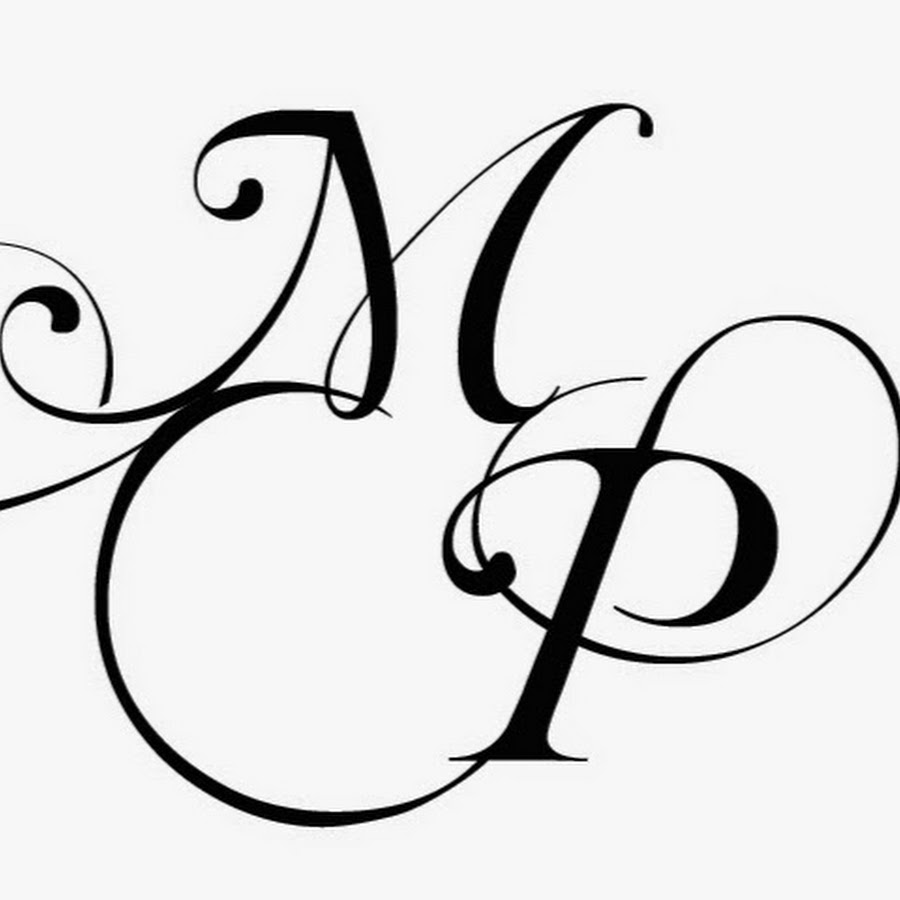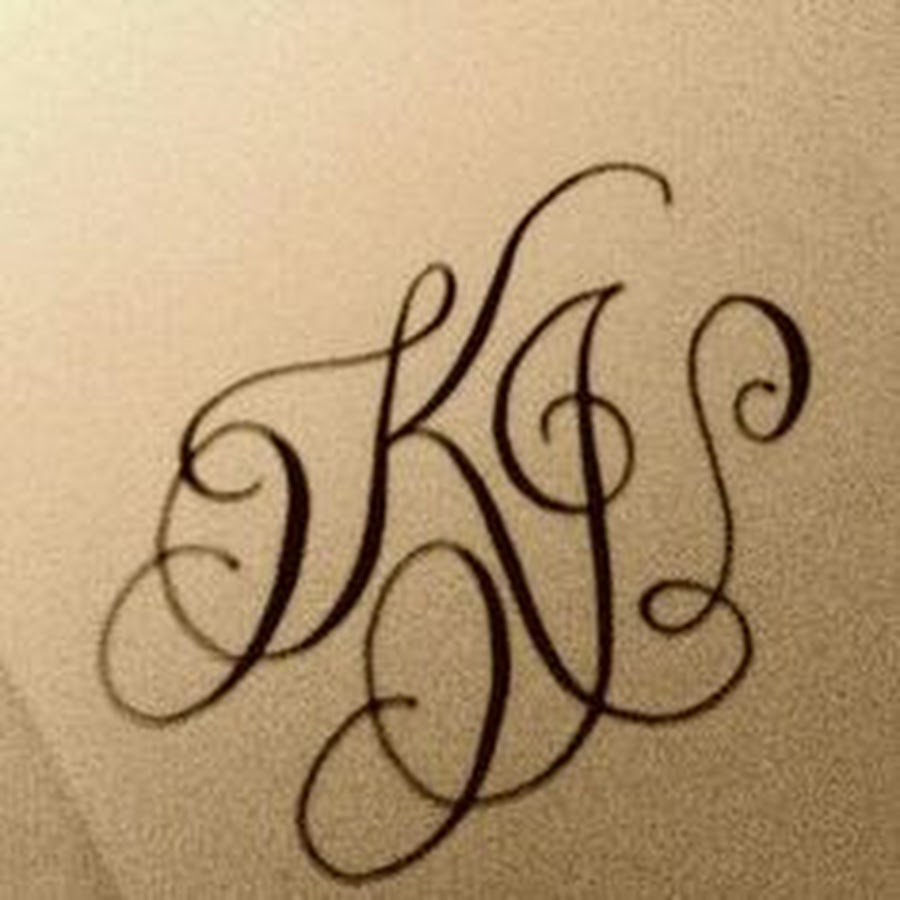
35 лучших бесплатных монограммных шрифтов для дизайнеров в 2019 году
С таким большим количеством великолепных (и бесплатных!) Шрифтов, доступных онлайн, действительно есть шрифт для любого случая. Хотя технически вы можете использовать любой шрифт для создания монограмм, некоторые шрифты специально разработаны и лучше подходят для этой цели. Монограммы — это большие декоративные буквы, используемые для персонализации различных видов рисунков. Вы можете использовать их для создания элегантных свадебных приглашений, профессиональных визиток, сложных канцелярских принадлежностей, брошюр, силуэтов или даже вашего собственного логотипа. Монограммные шрифты также отлично смотрятся в различных проектах DIY и в качестве шаблонов для машинной вышивки, и вы даже можете добавить их на свой веб-сайт, чтобы сделать текст более интересным.
Apex Lake сочетает в себе орнаменты с удобочитаемостью для отличных результатов.
2. ТраянусБрикс
Этот монограммный шрифт доказывает, что не все монограммные шрифты должны выглядеть так, как будто они были отправлены с 17-го века. TrajanusBricks — это современный геометрический шрифт, представленный в двух вариантах (на фото выше). Строчные буквы не имеют границы вокруг них, поэтому вы можете комбинировать их с заглавными буквами для некоторых действительно привлекательных эффектов.
3. FreeMonogram
4. Квадратные шапки
Как и в предыдущем шрифте, в Square Caps не так много глифов, но он восполняет это, добавляя уникальный штрих к заглавным буквам. Все они имеют иллюстрированный фон, и если вы присмотритесь, вы увидите, что они содержат разные детали. Благодаря этой креативной функции Square Caps будут отлично смотреться в книжке с картинками или в печатном сборнике сказок.
5. Генри Морган Хэнд
Генри Морган Хэнд выглядит просто, но его изгибы и штрихи отлично подходят для монограмм, которые должны быть читаемы. Он выглядит как рукописный шрифт, но он немного класснее обычного почерка.
6. Скрипт Freebooter
Freebooter Script с его тщательно продуманными штрихами выглядит великолепно и прекрасно работает как традиционный монограммный шрифт. Он также очень удобен для чтения, поэтому вы можете использовать его для написания целых абзацев, а не только инициалов. Он поддерживает некоторые расширенные символы.
7. Эксмут
Exmouth — еще один классический шрифт с монограммой. Он отлично смотрится как на экране, так и в печати. Это наклонный шрифт, который сочетает в себе тонкие и толстые линии для элегантного эффекта рукописного ввода.
8. Маленький лорд Фонтлеррой
Little Lord Fontleroy является популярным фаворитом в кругах DIY, скорее всего, из-за его эффекта контура, который позволяет легко переносить текстиль в качестве вышивки.
9. Sortefax
Вы получите много, если выберете Sortefax. Этот шрифт поддерживает большой набор символов и поставляется в трех одинаково очаровательных стилях с толстыми штрихами и тонкими штрихами. Это отличный шрифт для заголовков и инициалов в тексте.
10. Монотон
11. Preciosa
12. Debonair Inline
13. Ротенбург декоративный
Этот декоративный шрифт имеет отчетливый готический стиль, и инициалы действительно выделяются в любом виде текста. Ротенбург великолепен как традиционный шрифт с монограммой и вполне уместен, если ваш дизайн так или иначе связан с историей или фольклором.
14. Любители ссоры
Lovers Quarrel — это стильный скрипт-шрифт с богатой штриховкой символов в верхнем регистре.
Это выглядит потрясающе в монограммах для свадебных материалов, несмотря на зловещее название.
15. Парус
Парус читабелен и привлекателен своей простотой. Тонкие штрихи делают его разумным выбором для монограмм и инициалов, но вы также можете использовать его для заголовков и постеров.
16. Ицадзоке
Itsadzoke выпускается в нескольких стилях и поддерживает множество расширенных символов. Он хорошо выглядит как в заголовках, так и в инициалах, и наиболее интересной особенностью является способ смешивания строчных и прописных букв.
17. Рислинг
Этот стильный, тонкий шрифт просто излучает элегантность. Он не слишком богато украшен, поэтому он отлично подходит для минимального дизайна и чистых инициалов, а также для заголовков в журналах, например.
18. Черная роза
Черная роза толстая, ретро и строчные буквы очень аккуратные и читаемые.
Это будет отлично смотреться как в формальном, так и в повседневном дизайне
19. Кэррингтон
Carrington — это наклонный шрифт с ретро-штрихами и завитками. Он богато украшен и отлично подходит для монограмм, но также удобочитаем и отлично подходит для заголовков и логотипов.
20. Caslon Initials
Этот популярный монограммный шрифт поставляется в двух вариантах — обычном и каллиграфическом, так что вы можете комбинировать их для усиления визуального эффекта. Он декоративный, но не слишком богато украшенный, поэтому будет хорошо смотреться во всех типах дизайна.
Письменные и декоративные шрифты — отличаются тонкой линией и часто сложной формой. С помощью декоративных шрифтов вы действительно сможете выделиться и выразить свой уникальный характер — ваш или вашей фирмы. Есть два основных типа декоративных шрифтов: